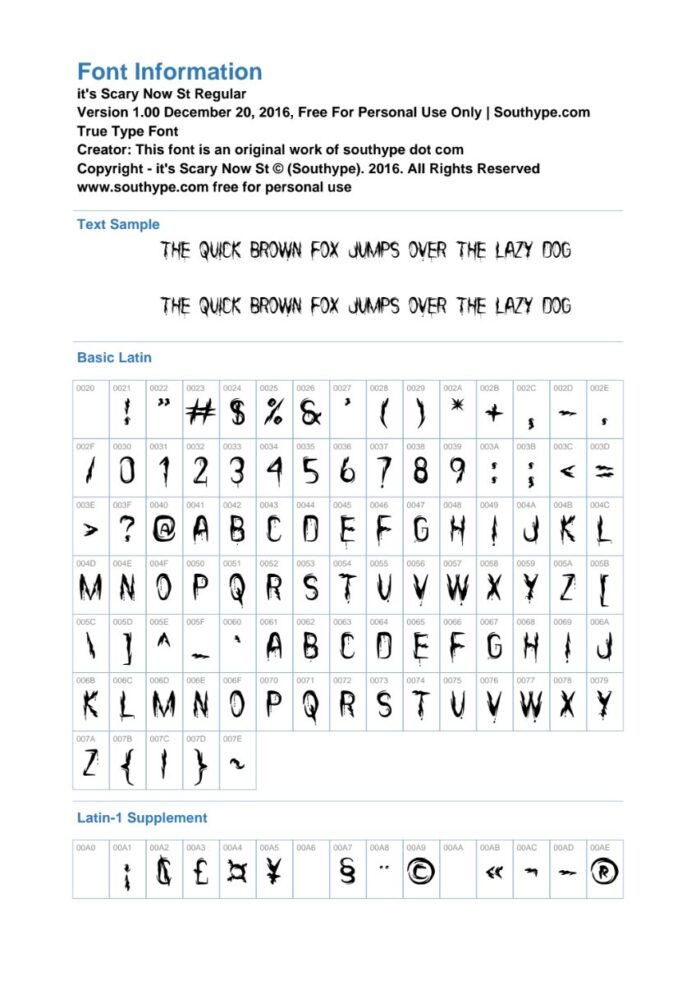
Font It’s Scary Now St – Halloween
Bạn đang tìm kiếm một phông chữ độc đáo, rùng rợn để tạo điểm nhấn cho các thiết kế Halloween, phim kinh dị hay sự kiện ma quái? Font It’s Scary Now St chính là lựa chọn hoàn hảo dành cho bạn. Với thiết kế đầy ám ảnh và phong cách đặc trưng, phông chữ này sẽ biến mọi ý tưởng của bạn thành hiện thực một cách ấn tượng nhất.
Giới thiệu về Font It’s Scary Now St
Font It’s Scary Now St là một kiểu chữ được thiết kế đặc biệt để gợi lên cảm giác kinh dị, bí ẩn và ma quái. Với những nét chữ không đều, sắc cạnh và có phần méo mó, phông chữ này mang đến một vẻ ngoài như được viết tay vội vã trong bóng tối, hoặc như những vết cào xước trên tường cũ. Đây là một tài nguyên đồ họa không thể thiếu cho những ai muốn tạo ra các sản phẩm có chủ đề kinh dị, Halloween, hoặc bất kỳ sự kiện nào cần một chút không khí rùng rợn.
Đặc điểm nổi bật của Font It’s Scary Now St
• Phong cách kinh dị độc đáo: Mỗi ký tự đều được thiết kế tỉ mỉ để truyền tải sự sợ hãi và bí ẩn, từ những đường nét sắc nhọn đến các chi tiết nhỏ tạo cảm giác cũ kỹ, đáng sợ.
• Tính linh hoạt cao: Phù hợp cho nhiều loại hình thiết kế khác nhau như poster phim kinh dị, banner quảng cáo Halloween, thiệp mời sự kiện ma quái, bìa sách, logo game, và nhiều hơn nữa.
• Tạo ấn tượng mạnh mẽ: Phông chữ này giúp thu hút sự chú ý ngay lập tức và để lại ấn tượng khó phai trong tâm trí người xem.
Ứng dụng của Font It’s Scary Now St trong thiết kế
Font It’s Scary Now St có thể được sử dụng trong vô số các dự án sáng tạo. Dưới đây là một số gợi ý:
Thiết kế Halloween
Đây là ứng dụng rõ ràng nhất. Từ thiệp mời, poster sự kiện, trang trí nhà cửa, đến thiết kế trang phục, Font It’s Scary Now St sẽ giúp bạn tạo ra một không khí Halloween chân thực và đáng sợ. Hãy tưởng tượng những dòng chữ “Happy Halloween” được viết bằng phông chữ này, chắc chắn sẽ khiến mọi người phải rùng mình.
Poster và banner phim kinh dị
Các nhà làm phim và quảng cáo có thể tận dụng phông chữ này để tạo ra các poster, banner, và tiêu đề phim kinh dị gây ám ảnh. Nó giúp truyền tải ngay lập tức thể loại và không khí của bộ phim, thu hút khán giả yêu thích thể loại này.
Thiết kế game và truyện tranh
Đối với các nhà phát triển game hoặc họa sĩ truyện tranh, Font It’s Scary Now St là một công cụ tuyệt vời để tạo ra các tiêu đề, hộp thoại hoặc hiệu ứng chữ đặc biệt, tăng cường trải nghiệm kinh dị cho người chơi và độc giả.
Sự kiện và bữa tiệc theo chủ đề
Nếu bạn đang tổ chức một bữa tiệc hoặc sự kiện theo chủ đề kinh dị, ma quái, phông chữ này sẽ giúp bạn thiết kế các vật phẩm trang trí, thiệp mời, và bảng hiệu một cách chuyên nghiệp và ấn tượng.